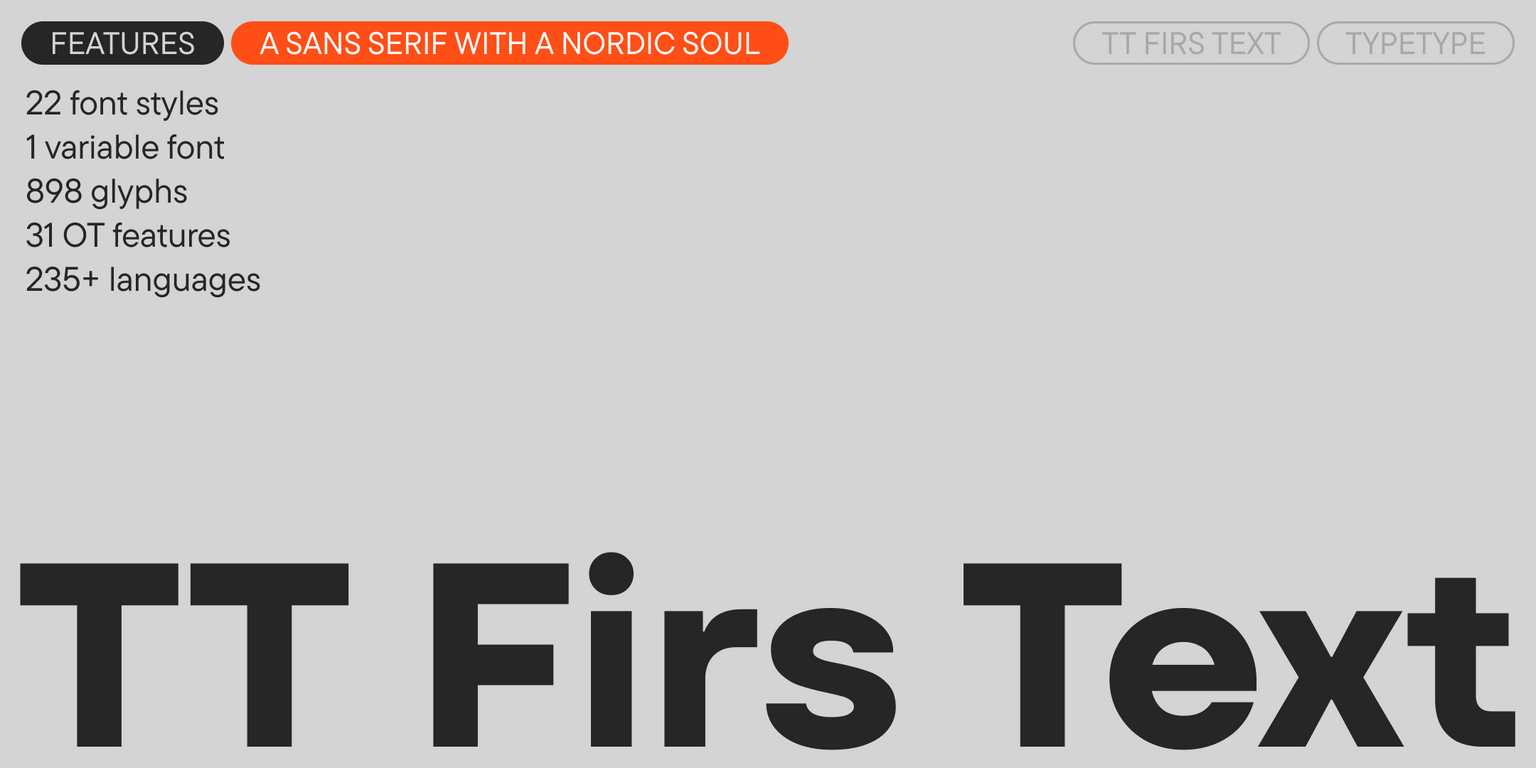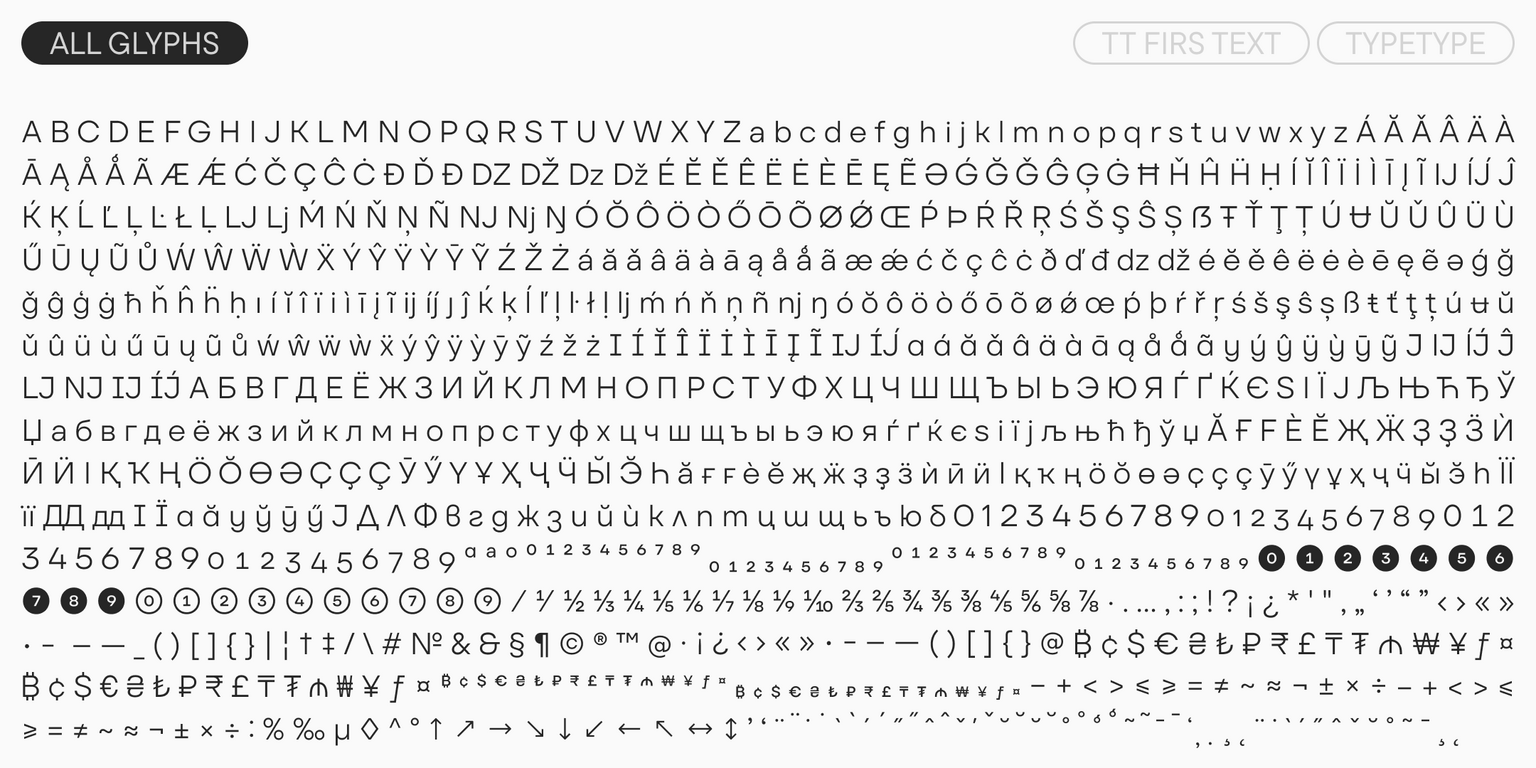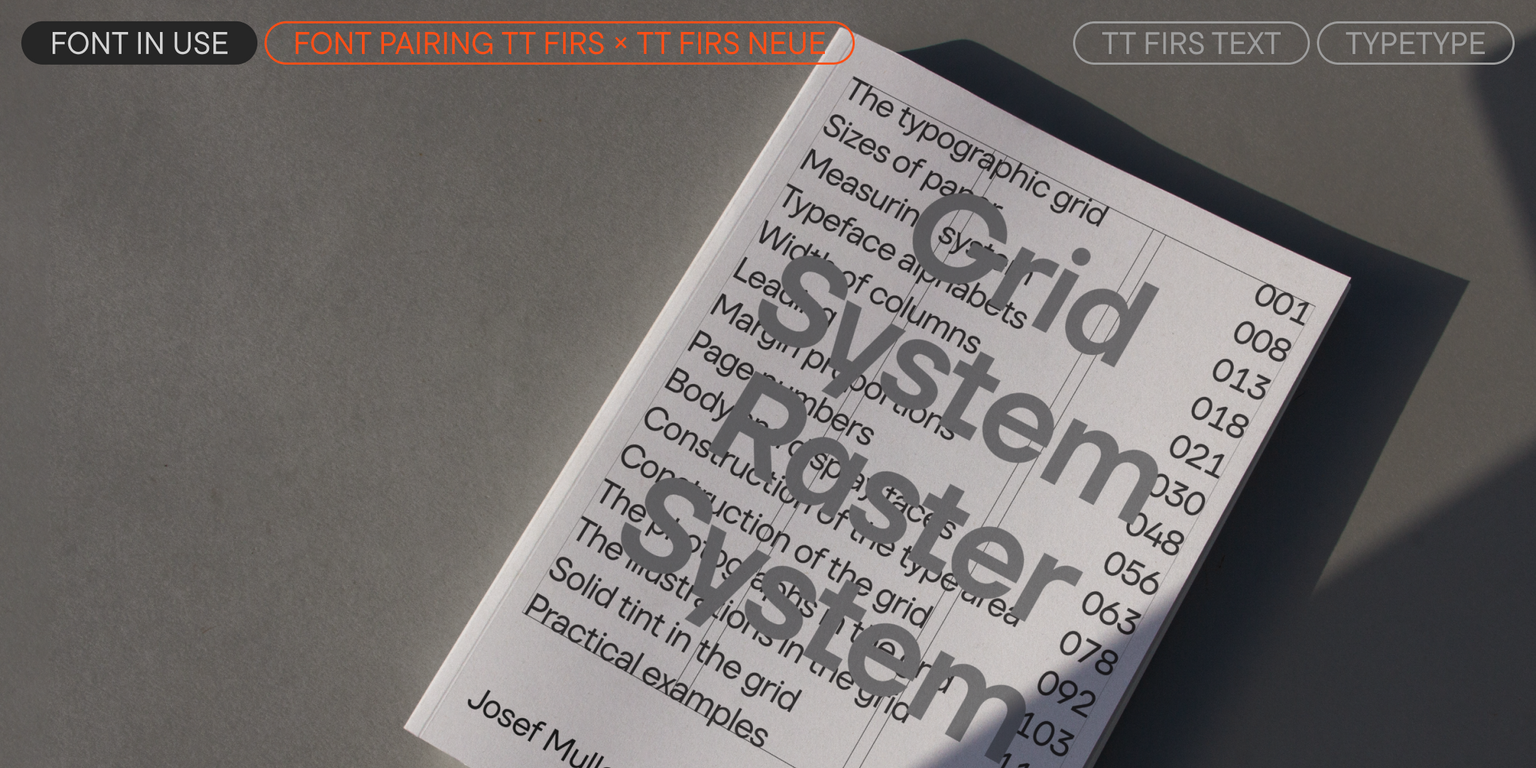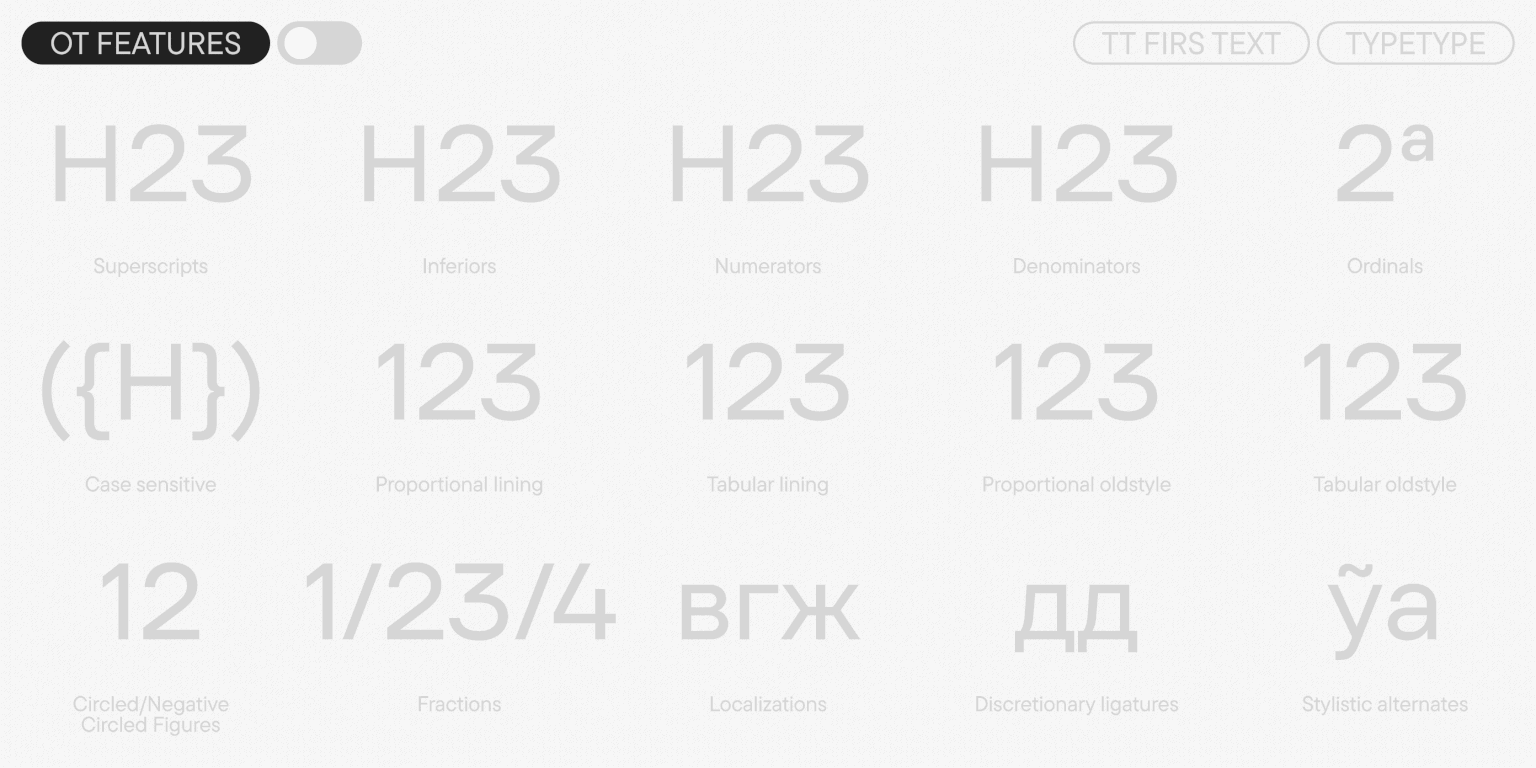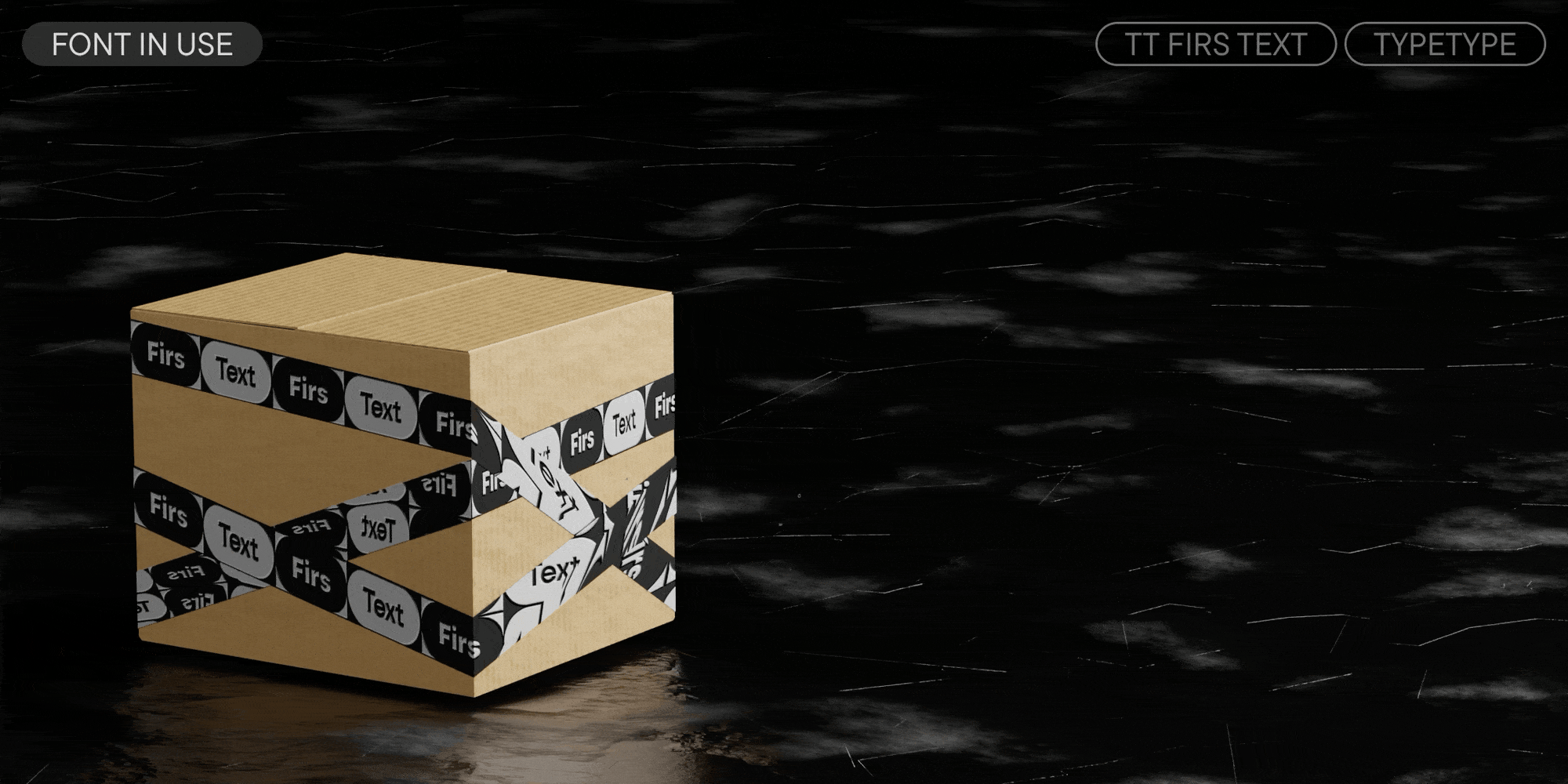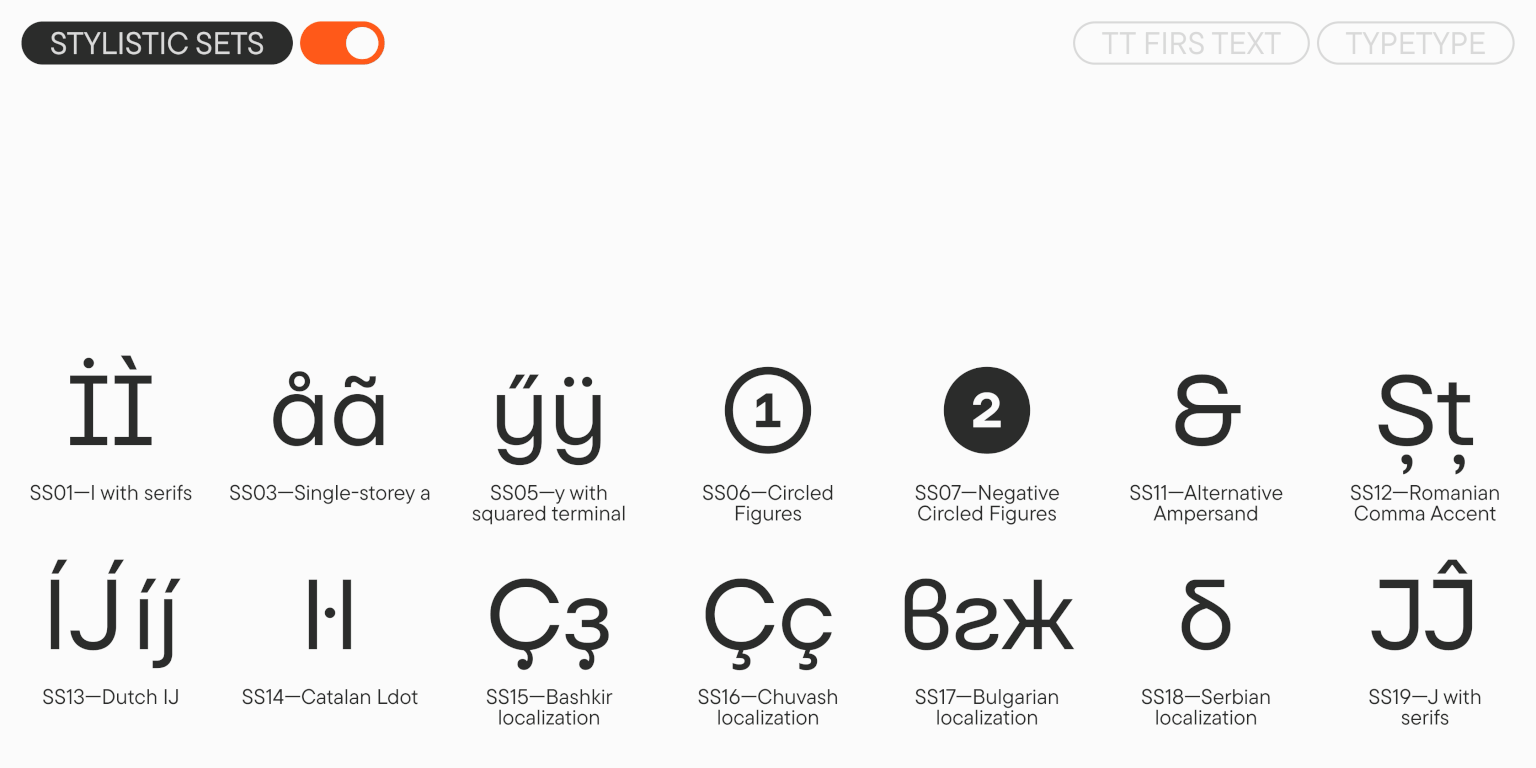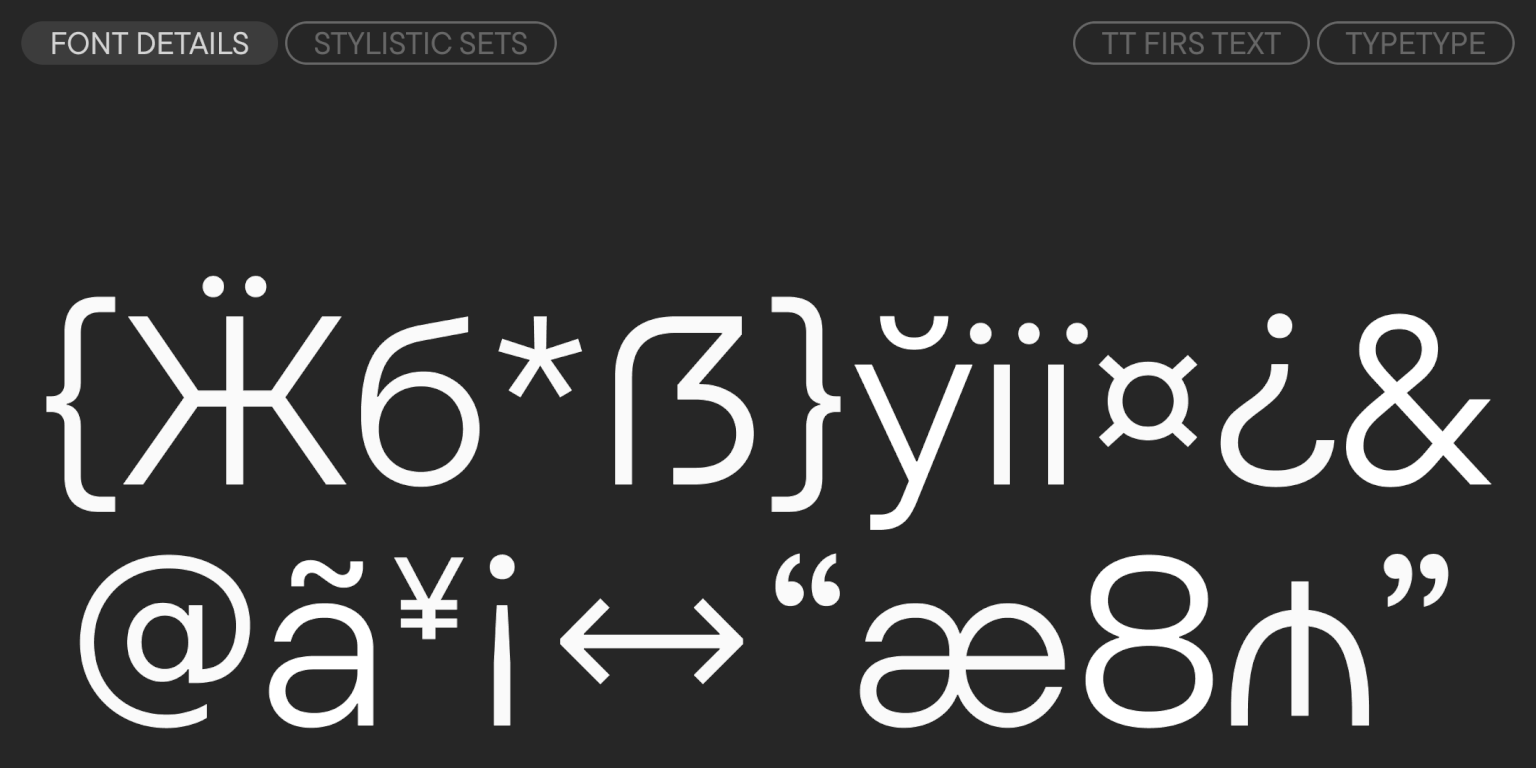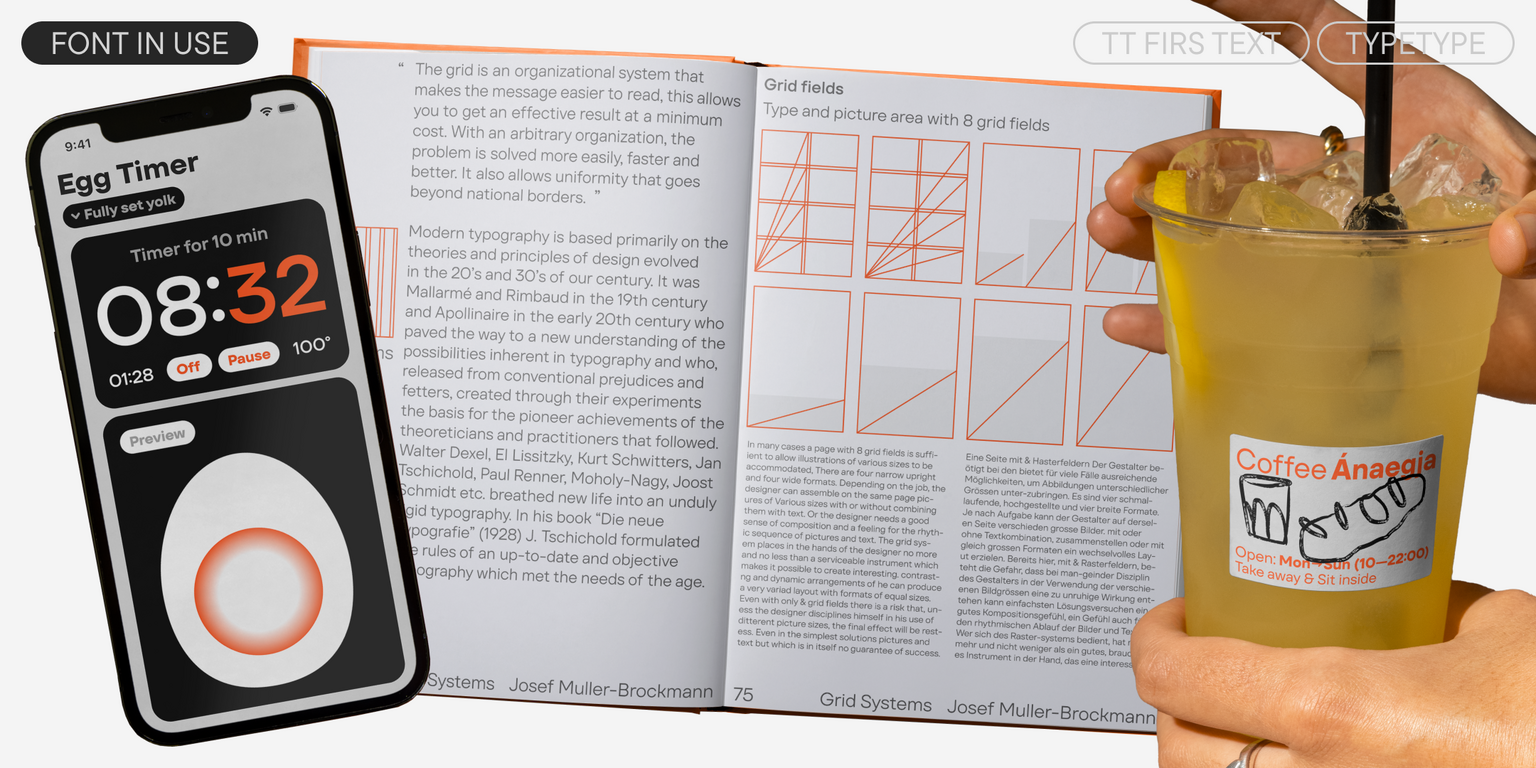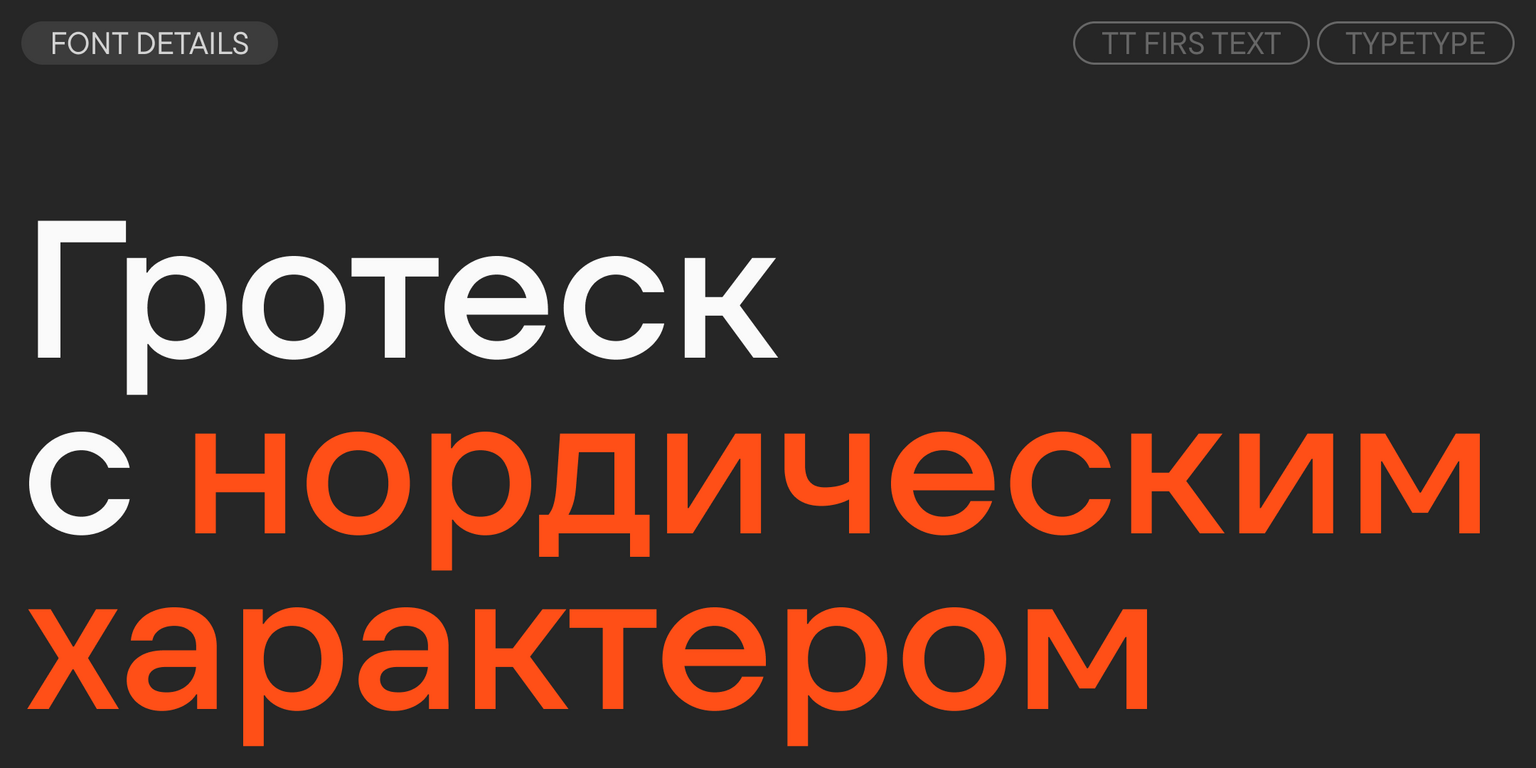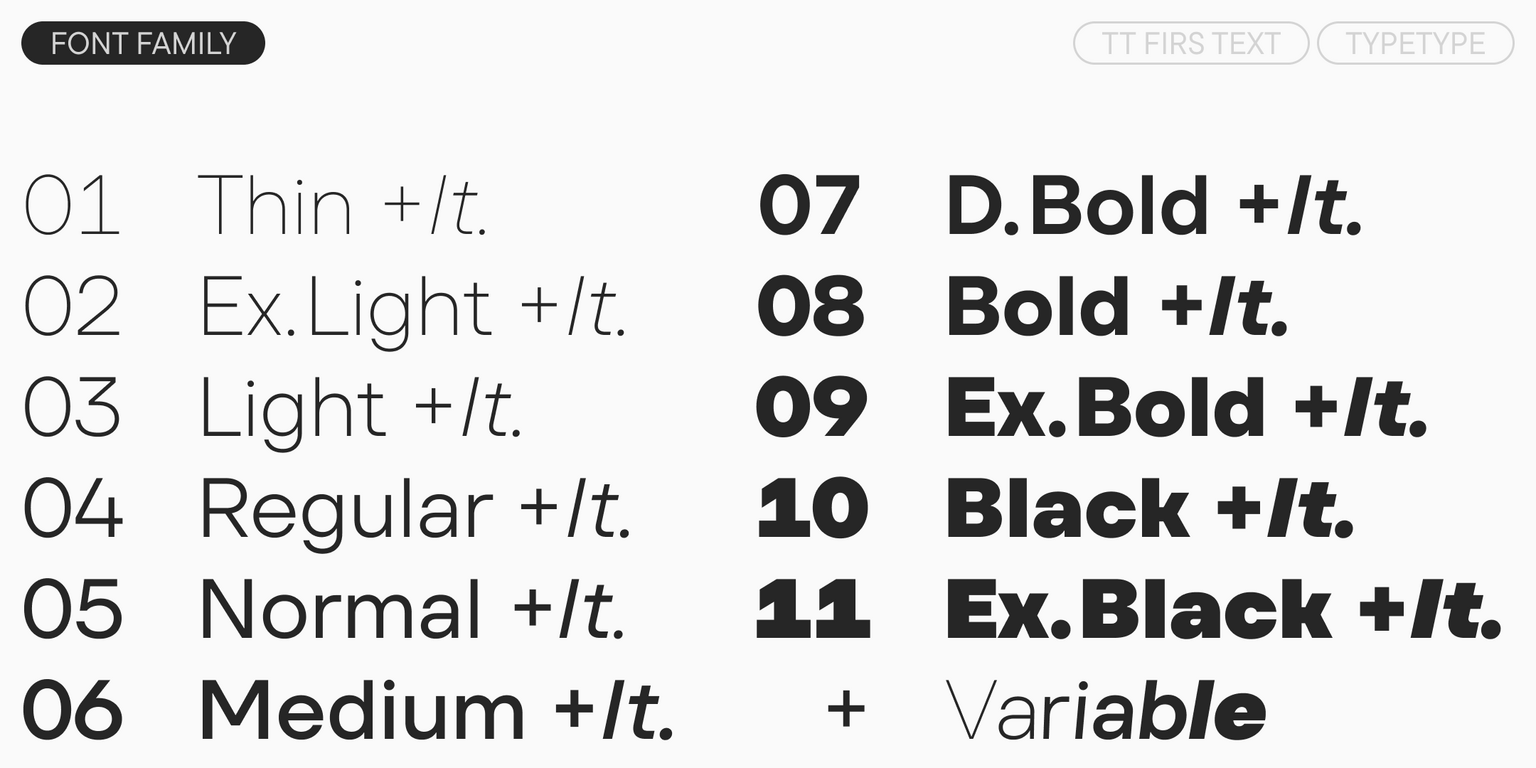
TT Firs Text
TT Firs Text — ТТ Фирс Текст
Произносится «ТТ Фирс Текст». «Фирс» — производное слово от fir, в переводе с английского «ель». «Text» — в переводе с английского «текст». Буквы «TT» являются аббревиатурой названия компании.
TT Firs Text — лаконичный геометрический гротеск с нордическим характером. Это универсальный, при этом выразительный текстовый шрифт.
TT Firs Text — скандинавский гротеск, который вы полюбите
Что касается характера нового шрифта, то мы постарались сделать его максимально нейтральным. За основу нового шрифта мы взяли новую версию TT Firs Neue, которую мы выпустили в 2023 году. Все сверхакцидентные элементы из шрифта мы полностью перерисовали и сделали более традиционными. TT Firs Text отлично подойдет для всех современных сфер использования.
Геометрический, текстовый, нордический
Малыш и Карлсон, который живёт на крыше
Jysk & Ikea
Знакомьтесь: TT Firs Text — лаконичный геометрический гротеск с нордическим характером!
TT Firs Text — текстовый шрифт, который создавался на основе обновленной в 2023 году гарнитуры TT Firs Neue. Мы стремились сделать его более нейтральным, но при этом наделить собственным неповторимым стилем. Подробнее о процессе разработки гарнитуры читайте в статье.
TT Firs Text получился одновременно холодным и элегантным, строгим и завораживающим, а главное — максимально универсальным. Мы сохранили эстетику скандинавского минимализма, но полностью перерисовали все выразительные элементы, сделав их более мягкими и традиционными. Набор текста стал более однородным, благодаря чему шрифт остается разборчивым и читаемым даже при наборе массива текста маленьким кеглем.
Этот шрифт одинаково хорошо подойдет для использования на веб-сайтах, вёрстки книг, брендинга и дизайна упаковки, оформления плакатов и афиш. Сфера его применения практически безгранична. TT Firs Text отлично работает в паре с TT Firs Neue, однако благодаря нейтральному характеру он легко сочетается и с другими шрифтами.
В TT Firs Text входит:
• 23 начертания: 11 прямых, 11 наклонных и 1 вариативный шрифт;
• 898 знаков в каждом начертании, в том числе знаки расширенной латиницы и кириллицы;
• 31 OpenType фича, в том числе нумераторы в кружках и стилистическая альтернатива для амперсанда;
• Поддержка более 240 языков.
TT Firs Text — для текстов со скандинавским оттенком!
ss01 | I with serifs
ss03 | Single-storey a
ss05 | y with squared terminal
ss06 | Circled Figures
ss11 | Alternative Ampersand
case | Case Sensitive Forms